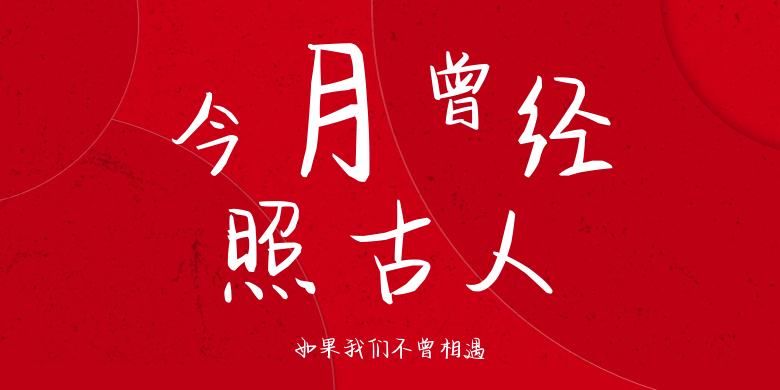
如果我们不曾相遇
如果我们不曾相遇,这款字体结构工整、笔画清晰,兼顾美观与易读性,适用于标题、正文、海报、包装、LOGO 等多种场景。字形优雅稳定,风格百搭耐看,适配日常排版与创意设计,让文字呈现更舒适、更具质感。如果我们不曾相遇一笔一画,皆是细节,以均衡的比例、流畅的线条打造舒适视觉体验,字形端正大气,风格简约现代。无论是商业设计、品牌宣传还是日常排版,都能轻松驾驭,让文字更有格调与力量。如果我们不曾相遇字体下载。